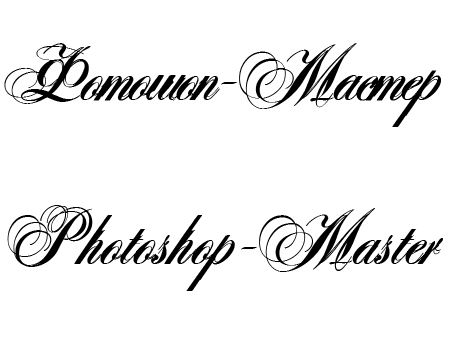
Ну вот, буквально за 10 минут фотка полностью преобразилась благодаря шрифту Антонэлла! Спасибо спасибо не устану говорить, ведь Папа может! Ну вобщем вот фотка, Antonella в тексте пожеланий...
Шрифт виден только когда он большого размера. :(
глаза напрягаются, чтобы это раздвоение прочесть, или это у меня одной двоится?)))))))))
Красиво. Команде ресурса - риспект и уважуха (шрифт здесь - 2-3-4-5-6-7-8-9-степенное).